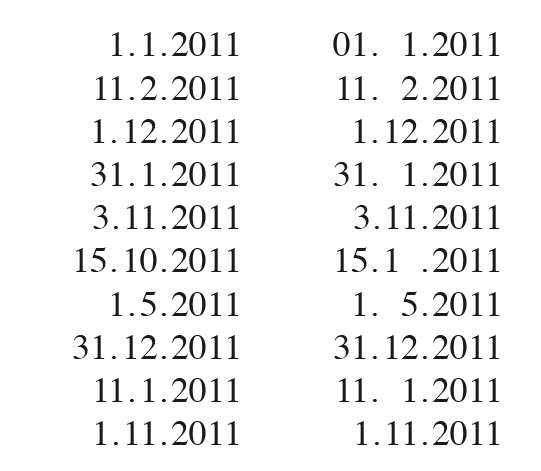
einer Zahl eine Null voranstellen
ich habe eine generelle Frage und zwar in Tabellenziffern, ob man einer Zahl eine Null voranstellen darf?
z.B.
05 %
10 %
:kopfkratz: Ob man das darf ...? Ich würde es nicht tun; die Zahlen sollten in der Tabelle ohnehin rechtsbündig sein, dadurch stehen die dann korrekt untereinander – die Lesbarkeit wird dann durch die einzelne Ziffer eher erhöht, weil man auf den ersten Blick sieht, dass es ein Wert unter Zehn ist ...
Worum geht’s denn genau? Um eine Tabelle? Im gewöhnlichen Fließtext sollte man einer Zahl keine Null voranstellen.
… einer Zahl eine Null voranstellen …
Das ist weder üblich noch notwendig. Zudem verschlechtert es die Lesbarkeit.
soviel ich weiß, ist eine führende Null nur in Tabellen und juristischen Texten zulässig. Von letzteren weiß ich nichts und bei ersteren braucht man sie bei Rechtsbündigkeit auch nicht.
Was ist mit Datumsangaben?
Auch da hat sie nichts verloren.
Falsch: 01.05.2012
Richtig: 1. 5. 2012
Der Duden empfiehlt ein schmales Leerzeichen zwischen Tag und Monat und ein normales Leerzeichen zwischen Monat und Jahr. Ich verwende lieber für beides ein schmales.
Ich schreibe entweder 1. Mai 2011 oder 01.05.2011 – letzteres bevorzugt in Geschäftsberichten, weil der Großteil der Kunden das so vorgibt und weil das lt. DIN 5008 erlaubt, wenn auch typografisch nicht korrekt, ist.
1. Mai 2011
Das könnte auch sehr gut die sinnvollste Schreibweise sein, da sie, ohne dass man um Konventionen und Normen weiß, definitiv eindeutig ist, was Tag und Monat angeht :)
Und die hübscheste im Fließtext ist sie noch dazu. :gimmifive:
Falls Rechtsbündigkeit aus Software- oder anderen Gründen nicht möglich ist, bietet sich mglw. noch das ziffernbreite Leerzeichen U+2007 an.
Das könnte auch sehr gut die sinnvollste Schreibweise sein, da sie, ohne dass man um Konventionen und Normen weiß, definitiv eindeutig ist, was Tag und Monat angeht :)
genau aus diesem Grund verwende ich dieses Format auch in deutschsprachigen Texten (techn. Spezifikationen, Prüfzeugnissen usw.) die sich an Leser richten, deren Muttersprache mir vorher nicht bekannt ist.
Die Tag- und Monatsangabe gilt (so denn numerisch) als Ordinalzahl und da steht keine Null vor.
Vielleicht auch passend dazu:
Auf einem Grabstein ist es nicht üblich 01.05.2010 zu schreiben.
Trotzdem kommen ab und an Kunden und sagen, dass dies heutzutage so geschrieben werde.
Vielleicht auch passend dazu:
Auf einem Grabstein ist es nicht üblich 01.05.2010 zu schreiben.
Trotzdem kommen ab und an Kunden und sagen, dass dies heutzutage so geschrieben werde.
Wer sich täglich an die DIN 5008 halten muss, dem geht das halt in Fleisch und Blut über. Es ist ja auch grundsätzlich richtig.
Ob das richtig ist, ist die Frage ... Richtig ist es eigentlich ja nur, wenn die Null etwas ausdrückt was nicht vorhanden ist, also beispielsweise bei 101, wo kein Zehner vorhanden ist, oder bei Nachkommastellen; eine Null als erste Ziffer einer Zahl ist prinzipiell unsinnig ... :-?
… eine Null als erste Ziffer einer Zahl ist prinzipiell unsinnig ...
Sie ist unsinnig, unschön, überflüssig, aber trotzdem ist sie richtig. In Tabellen ist sie sogar notwendig um die Lesbarkeit sicherzustellen, da ist sie prinzipiell sinnig. Zum Glück sind wir aber nicht gezwungen sie überall als führende Null zu verwenden. :trost:
Vielleicht auch passend dazu:
Auf einem Grabstein ist es nicht üblich 01.05.2010 zu schreiben.
Trotzdem kommen ab und an Kunden und sagen, dass dies heutzutage so geschrieben werde.
Wer sein Dasein stets in einem tabellarischen Lebenslauf geordnet hatte, möchte vielleicht auch DIN-gerecht Bilanz ziehen … ;-)
Erkläre …
Die Orientierung mit der führenden Null ist wesentlich einfacher …
Das ist keine Erklärung, die einen Widerruf überflüssig machte. Das sieht nur deswegen so gruselig aus, weil die Abstände zwischen Tag / Monat und Monat / Jahr fehlen. Man könnte auch statt einer Führungsnull ein Halbgeviert setzen, dann würden die Punkte sauber untereinanderstehen.
… ein Halbgeviert setzen, dann würden die Punkte sauber untereinanderstehen.
Ja, ne, klar … sauber untereinanderstehen … Lesbarkeit …